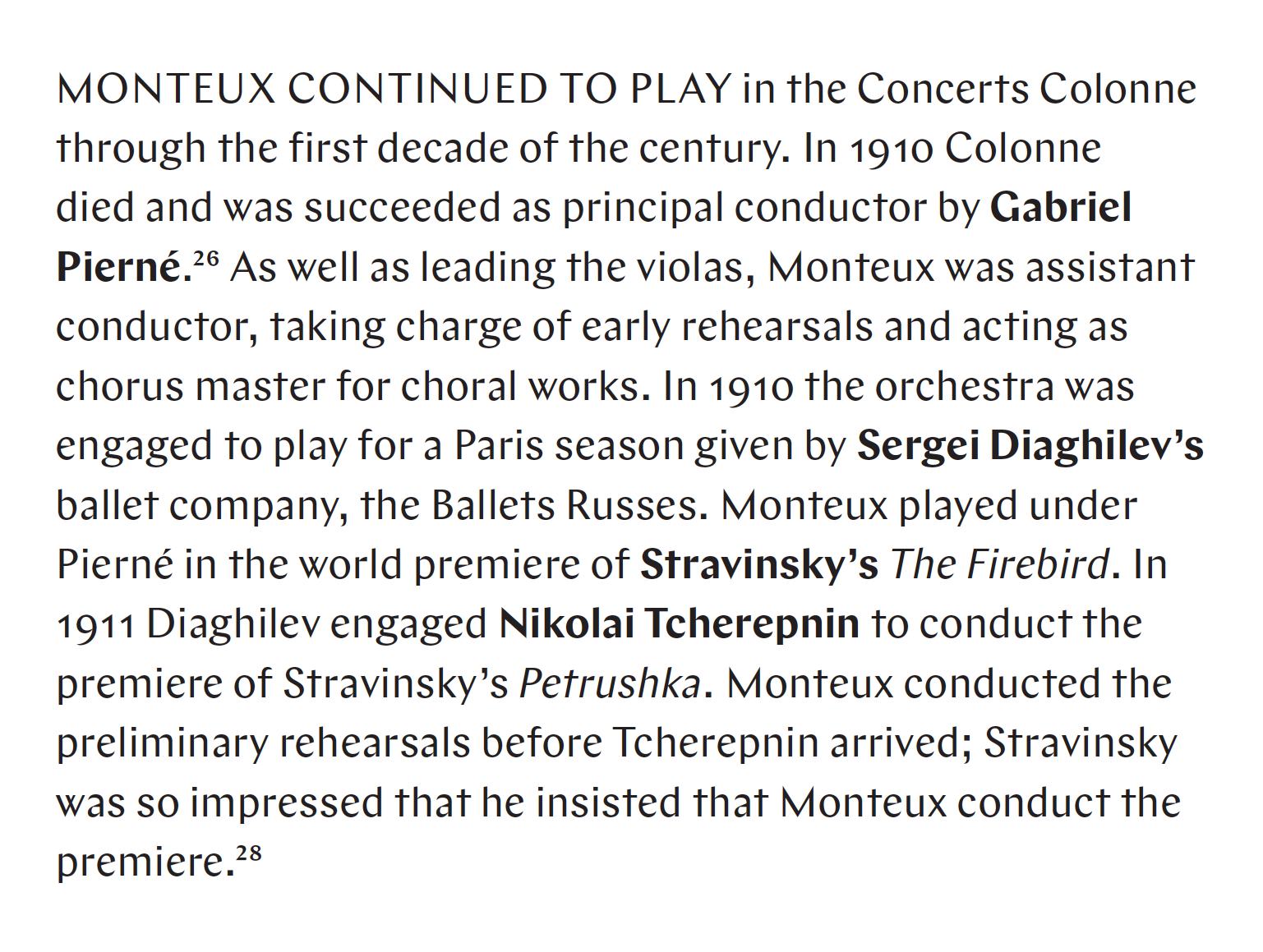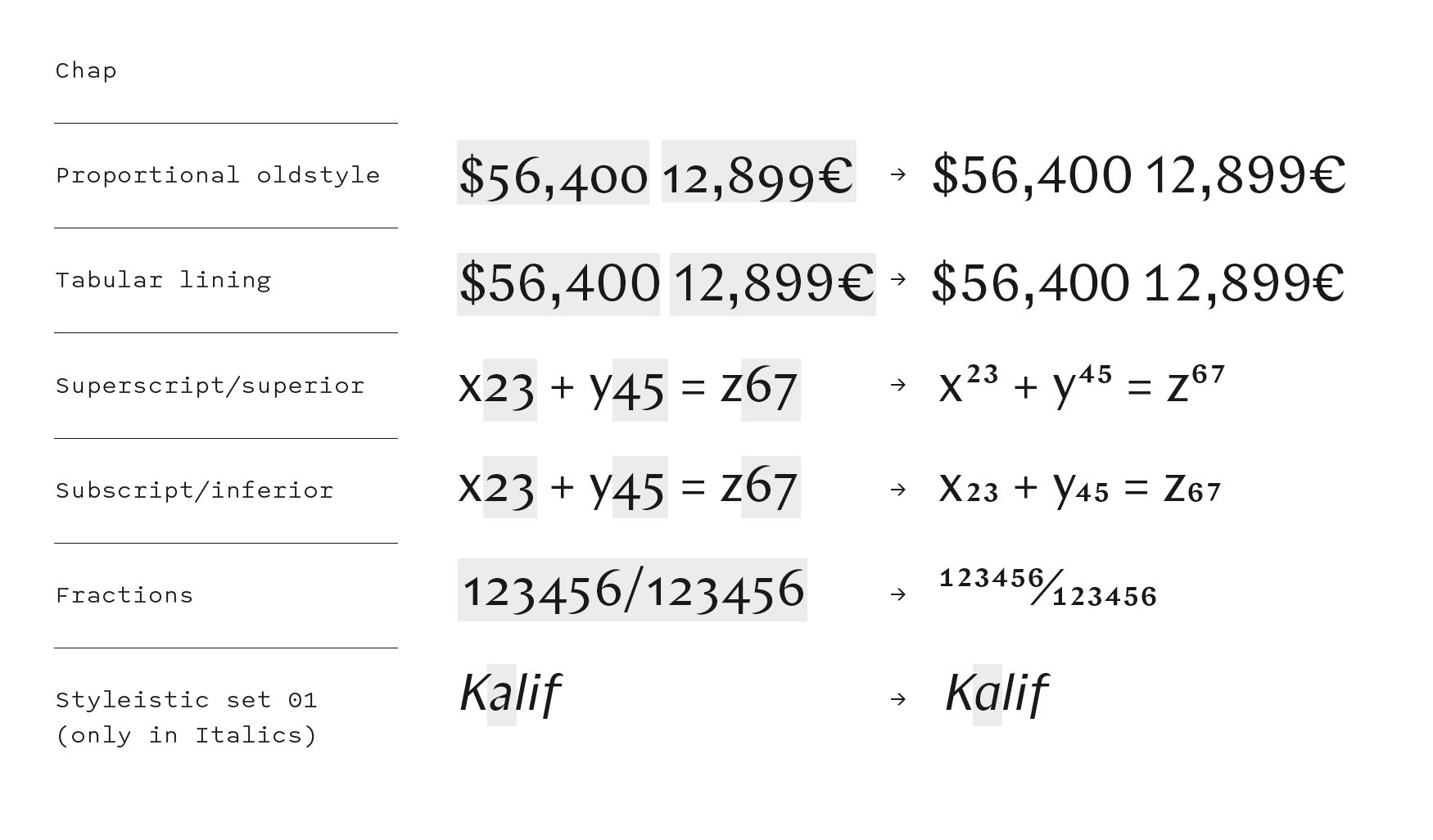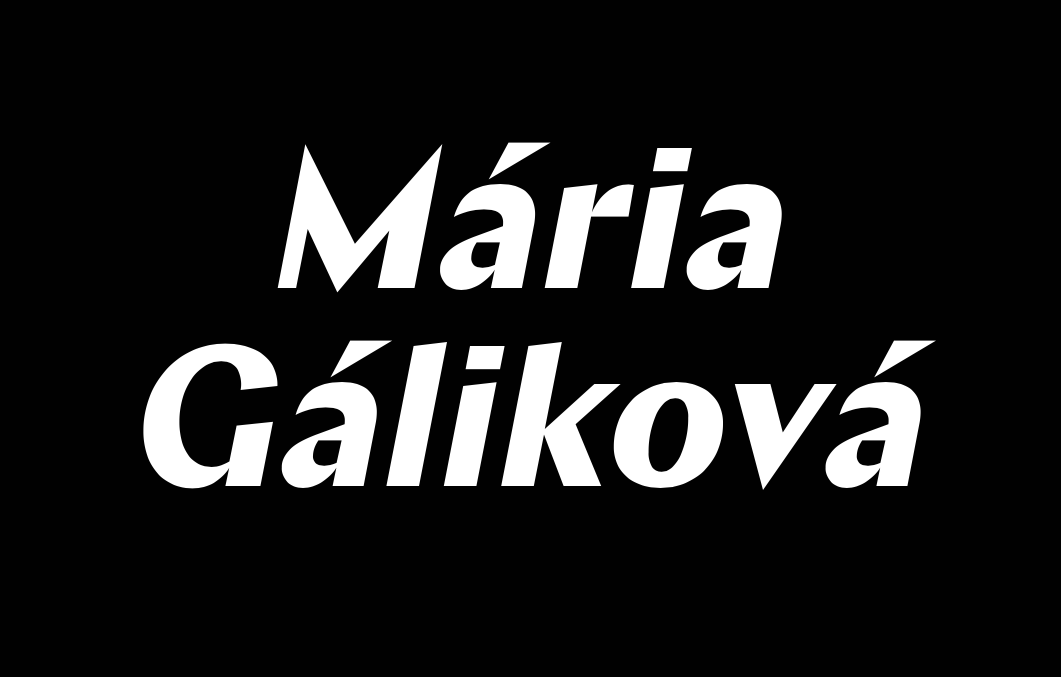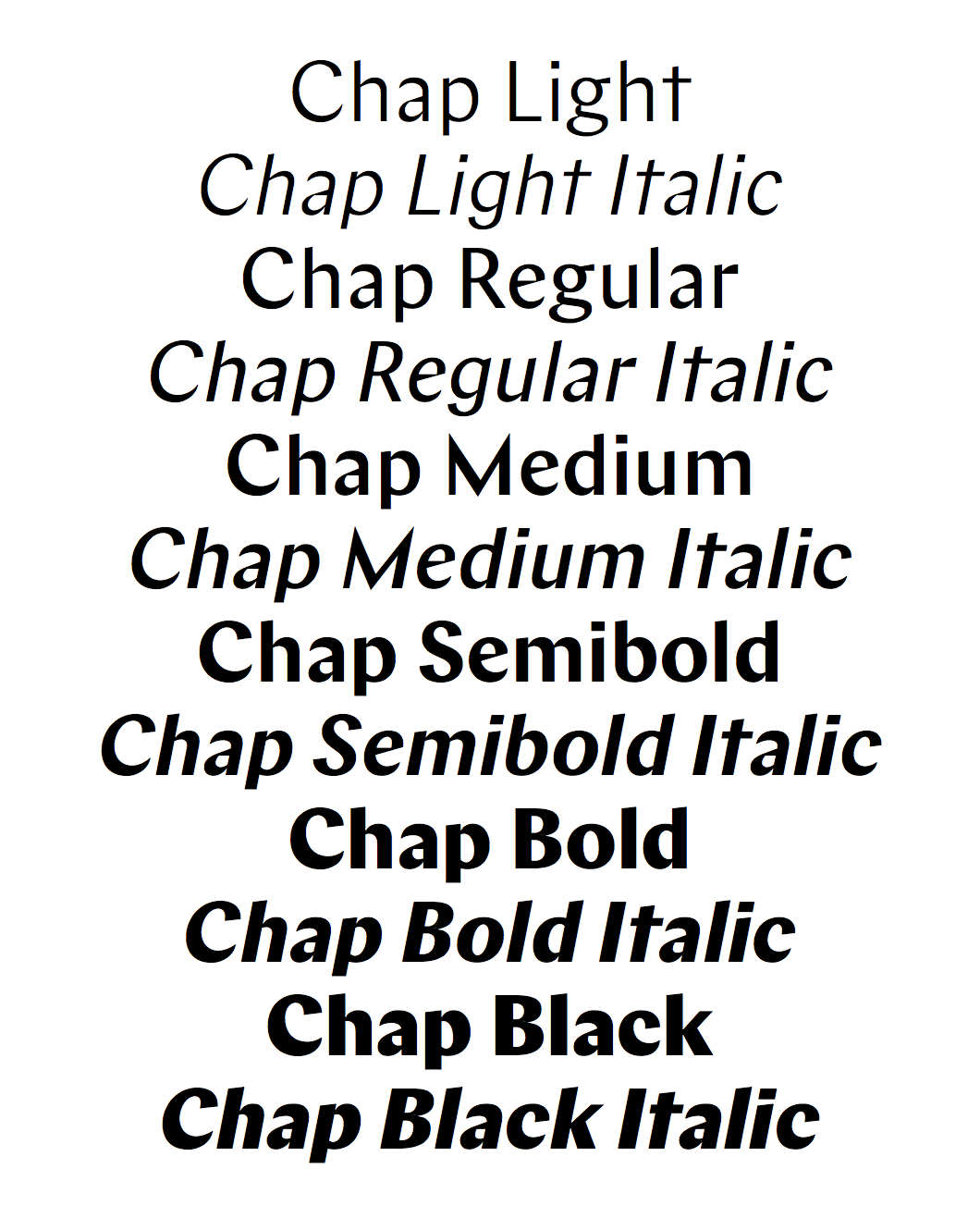
Die Geschichte der Groteskschriften des 20. Jahrhunderts ist eine Geschichte des allmählich abnehmenden Strichkontrasts. Serifenlose Schriften mit sichtbarem Kontrast waren in den 1920–50er Jahren sehr beliebt, als sie häufig für Werbung, Architekturbeschriftungen und Logos verwendet wurden. Dieser typografische Stil geriet mit der Übernahme der Spätmoderne aus der Mode und tauchte für die nächsten fünfzig Jahre allenfalls im Dienste der Neuheit oder Nostalgie wieder auf.
Ursprünglich für das Finnish Culture Institute in New York entworfen, würdigt Chap die kontrastreiche Sans-Tradition, vermeidet aber direkte Bezüge zu einem bestimmten Design. Im Gegenteil: seine Konstruktionsweise will Konventionen eher abstreifen. Die Linienführung bezieht sich im Allgemeinen auf die eines breiten Federhalters, aber nicht immer auf erwartete Weise. Es gibt ungewöhnliche Wendungen des Strichs und sogar Momente, in denen die Kalligraphie der Geometrie nachgibt. Chap ist ein Versuch zu zeigen, dass eine Sans mit Kontrast modern und aktuell sein kann. Sie ist eine Fontfamilie, die sich in einer Vielzahl von zeitgenössischen Umgebungen zu Hause fühlt, und doch nicht nur ein modisches Gesicht sein will. Anstelle von Trends, die mit der Display-Typografie verbunden sind, sucht Chap eine zeitlosere, funktionellere Ästhetik, indem Buchstaben gezeichnet wurden, die in lesbaren Textpassagen in allen Größen und Längen genutzt werden können. Dieses Mehrzweckziel spiegelt sich auch im großzügigen Gewichtsbereich (sechs plus Kursivschrift), den Zahlen für Text, Titel und Tabellen sowie im erweiterten lateinischen Zeichensatz wider.
Chap ist eine Mischung aus glatt und scharf, eine serifenlose Schrift mit einer neuen Kontrastidee für ein neues Jahrhundert.